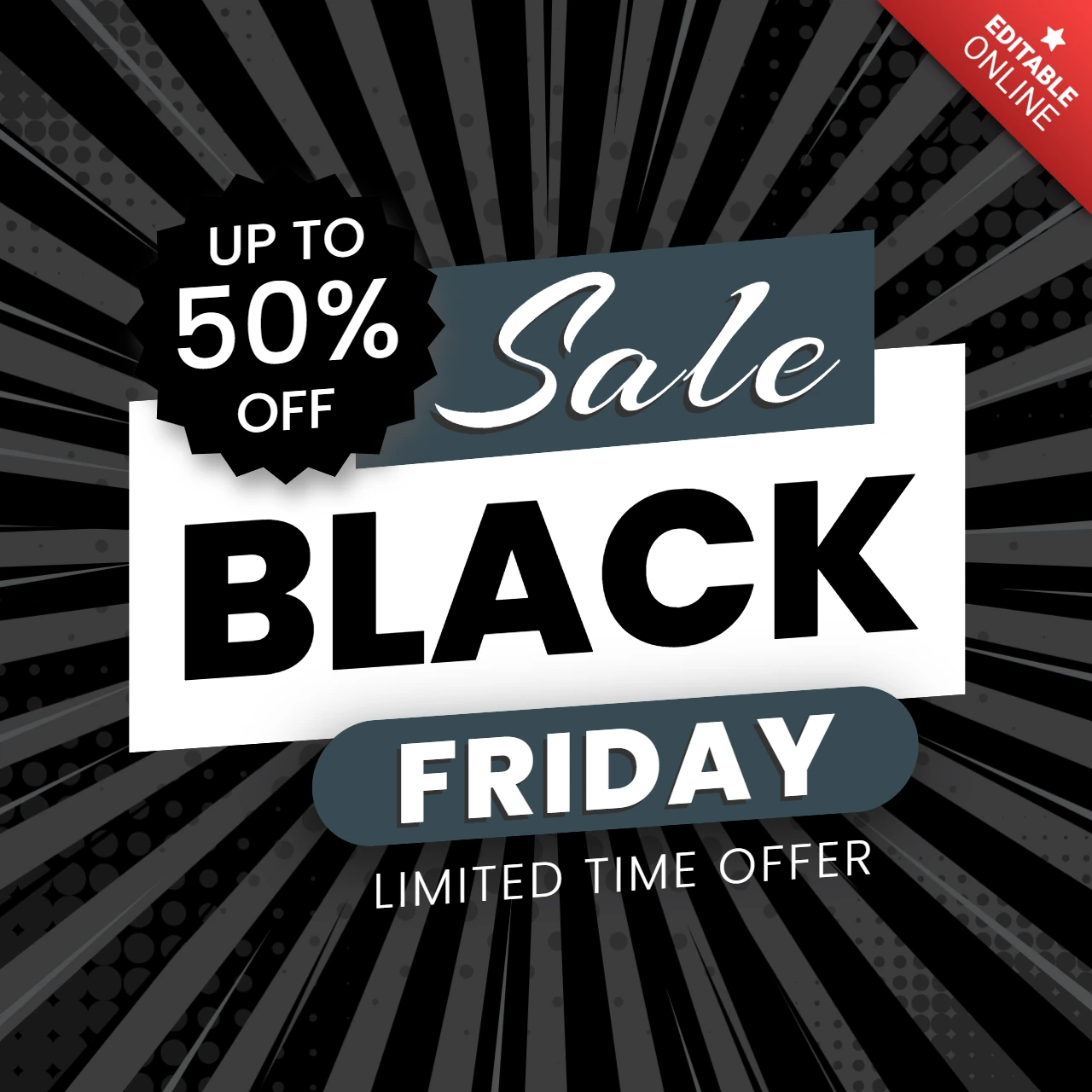
Modèle de design de vente du Black Friday avec une typographie audacieuse pour des flyers promotionnels
Éditer dans Design Studio Télécharger en JPGÉlevez votre jeu marketing ce Black Friday avec nos modèles de design audacieux pour des flyers promotionnels—profitez de votre réduction limitée dans le temps et créez des publicités époustouflantes pour vos offres de vente au détail !